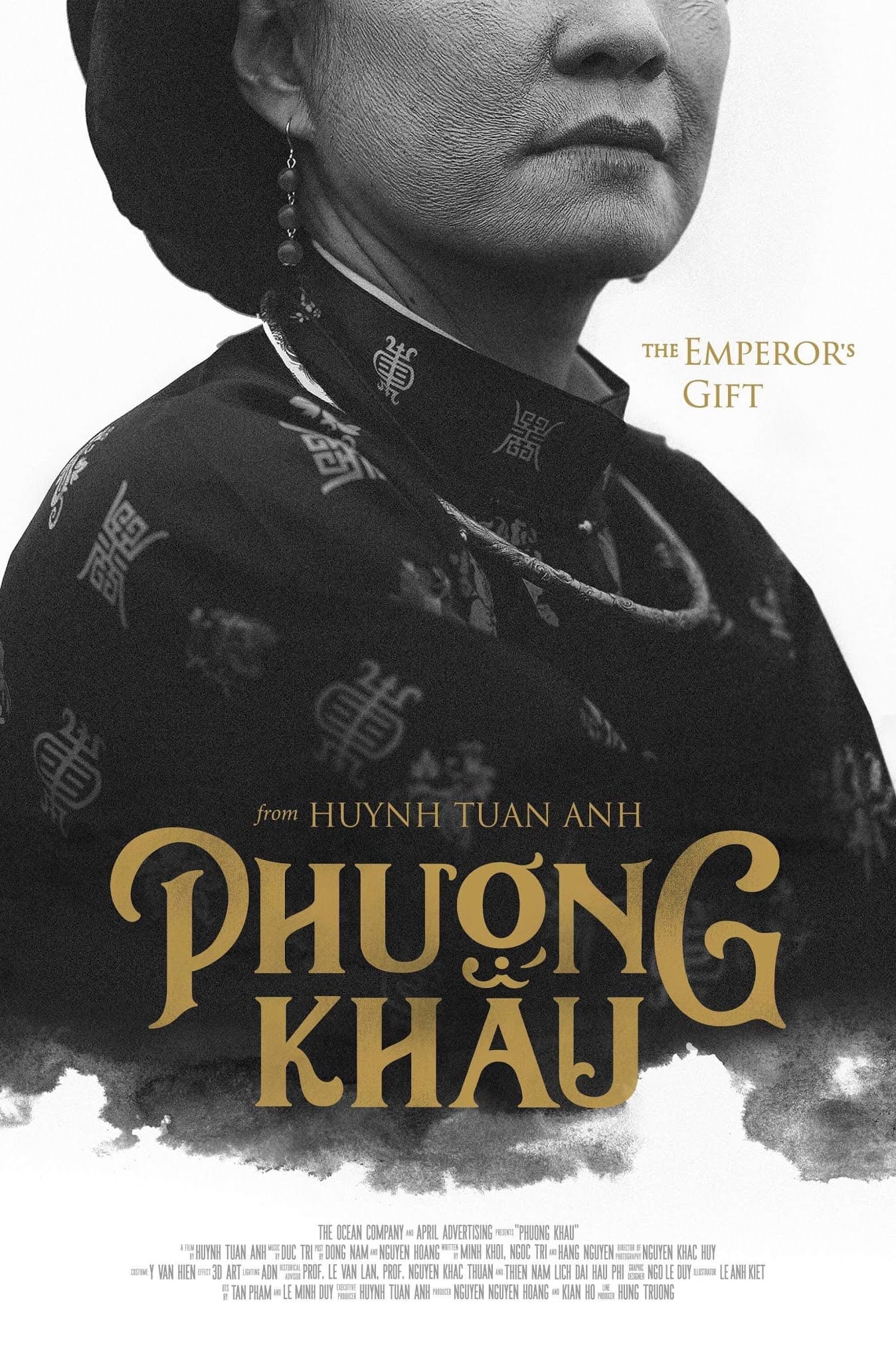
Có khá nhiều bạn có hỏi mình trên page là có biết font chữ phim Phượng Khấu là gì không? Hôm nay mà mình đã tìm được, đây là font nước ngoài có tên là Sacred Bridge và đã được Việt Hóa nên mình chia sẻ miễn phí đến các bạn.
Font Sacred Bridge Việt hóa là một kiểu chữ cổ điển, được tạo ra với phong cách in chữ và hiện đại, chữ thường và chữ nghiêng bao gồm nhiều trang trí và biểu tượng bổ sung. Sacred Bridge tuyệt vời cho bất kỳ loại mục đích thiết kế nào từ xây dựng thương hiệu, poster, tạp chí, biểu tượng, quảng cáo, áo phông, v.v.